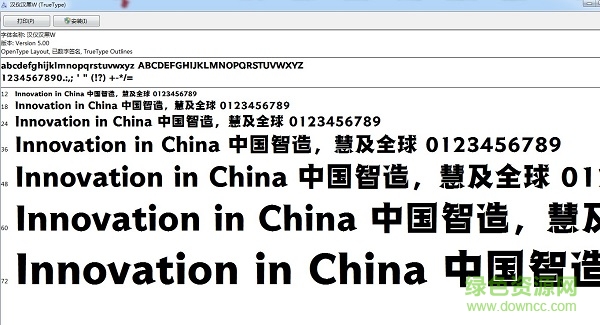
漢儀漢黑w字體是一款粗黑有力的漢儀字體,筆端較尖,黑白勻稱,字形顯眼,清晰度高,易于辨識(shí),比較容易給人留下強(qiáng)烈的印象,適合用作海報(bào)標(biāo)題標(biāo)或是招牌標(biāo)志,歡迎需要的朋友在綠色資源網(wǎng)免費(fèi)下載!
是中文一類字體的名稱,與白體相反,特點(diǎn)是沒有襯線裝飾,筆劃粗壯有力,撇捺等筆畫不尖,使人易于閱讀,由于其醒目的特點(diǎn),常用于標(biāo)題,導(dǎo)語,標(biāo)志等等。